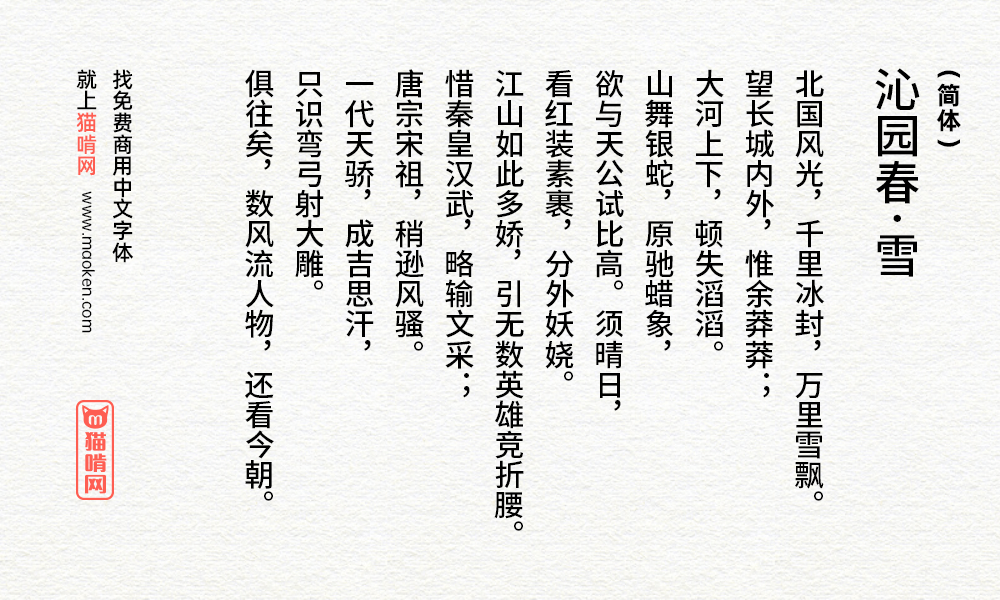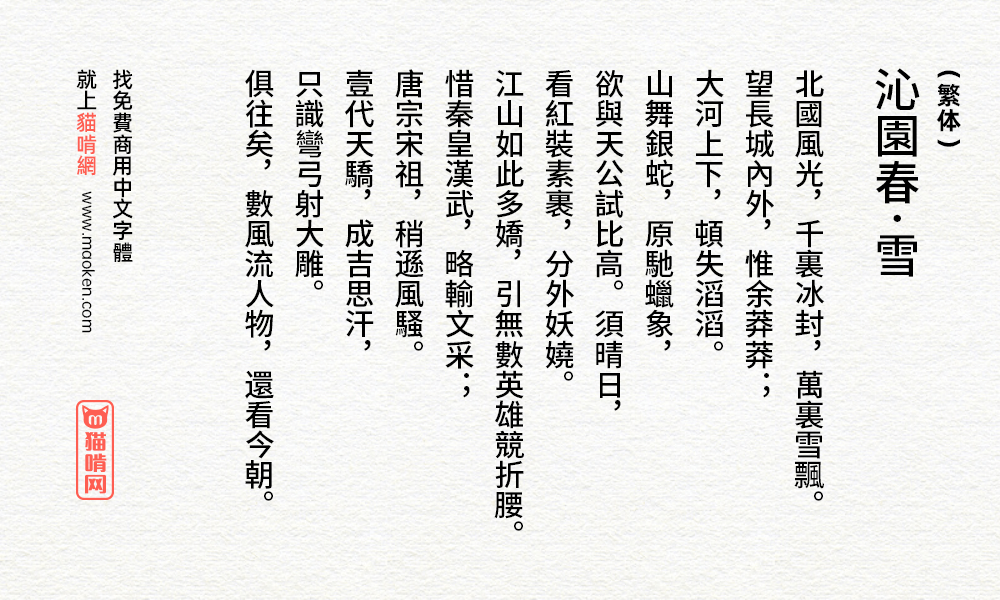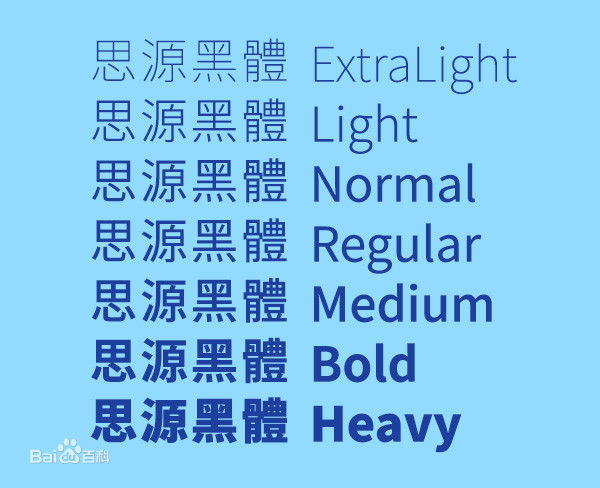
思源黑体:Adobe与谷歌开发的大名鼎鼎的免费商用字体
字体作者:Adobe & Google (美国) 字体字重:7个
思源黑体于2021年04月28日更新2.004版本,这个版本增加了思源黑体可变字体版本。关于思源黑体可变字体的介绍可以点击这里查看介绍。
说起思源黑体,也不用太多的介绍了,估计做设计的朋友们应该都会知道这款字体。这是Adobe与Google历时三年在2014年7月宣布推出的一款开源字体,这种字体有七种字体粗细(ExtraLight、Light、Normal、Regular、Medium、Bold 和 Heavy),完全支持繁体中文、简体中文、日文和韩文,这些全部都包含在一种字体中。
思源黑体有两个版本,一个是Adobe发布的版本,一个是谷歌发布的版本。这两个版本有什么不同呢?
1、字体名称不同
这两个版本的区别是字体的名称不同。Adobe版本在PS中显示的字体名称是“思源黑体”,而谷歌版本在PS中显示的字体名称是“Noto Sans CJK”
2、字重的名称不同
Adobe版本的字重名称是:ExtraLight、Light、Normal、Regular、Medium、Bold 、Heavy。
Google版本的字重名称是:Thin、Light、DemiLight、Regular、Medium、Bold、Black
关于本站提供的思源黑体行高修正版
只能说现在版本的思源黑体有些不太适合Android系统了,虽然Android原生支持可变字体是好事,但是有些情况下括号和句号会因为一些opentype特性叠在一起,这种显示效果并不好,而且看惯了某些厂商定制版字体再看思源黑体就会觉得这字体咋黏糊糊的,不过还是那句话,众多开源中文字体里面思源黑体仍是天花板……
思源黑体更新了2.005R版,但有了别的黑体,对思源黑体没啥兴趣了……
• 习惯了OPPOSANS的简洁、悠黑的完美灰度、荣耀SANS/小米兰亭pro的均匀骨架、冬青黑体的人文、苹方的六边形全能,再看思源的各种小缺点小瑕疵实在不习惯,现在开源领域的械黑/IBMPlexSans质量都比思源SC好,而且OPPOSANS/MiSans/荣耀SANS/阿里惠普都是免费商用的,字集大字重又多,不管哪方面思源都没任何竞争力了
• 只能说一开始中文字体市场正好缺一套免费的、质量还说得过去的字体,思源黑体一出现瞬间炸开了锅,但现在华米OV耀各自都定制了字体,个个都卷到极致,都免费商用,思源自然没什么优势了,再加上思源黑体的主导设计是小日子那边负责的,审美上本来就跟咱们不一样(这也就是你第一眼看它就不太顺眼的原因之一),还有我看到有人说冬青黑体,这冬青黑体更没必要提了,那玩意儿实际上比思源黑体还那啥,方正兰亭黑、汉仪旗黑的作者齐立还发文批评过,思源黑体的问题都没它严重,当年各大手机厂商也只有锤子看上冬青黑体,后面锤子自己都改用方正悠黑了,虽然后面腾祥、汉仪重新发布了7字重新版本,但是基本见不着实际使用的……
• 锤子没用方正悠黑,是把方正悠黑优化了下修改成锤子T黑,个人感觉质量比原版方正悠黑高很多,比如把不舒服的出脚衬线都去掉,更适合屏显,不过悠黑系的笔画竖勾里的脚实在不好看,又短又弯,软绵绵似的支撑不住重量
华文(就是那个代工中文版的)把常州的笔画丢尽了,相比日文版一大堆重心不稳+无意义修改。。。
• 没错,衍生自KR&JP版思源的源样黑体和SC版相比简直高下立判,华文早期给乔帮主做的华文黑体质量都比SC版思源好N倍,其实就是没用心
• 主要是华文把很多零部件原创了一遍,但你仍能感受到这是日文字体改的,属实是没必要,不过好在2.0版本修正了一些在1.0版里特别丑的,比如廴这个部首(估计是文鼎要做港版字形,顺道修复了一些偏旁部首),也有改砸了的,比如“对”、“叶”、“吔”(字形标准都弄错了)“坏”(本来没啥,就是日版也不好看),只希望3.0版能再掰回来一些吧,顺道把真正没必要改的给掰回去(有文鼎操刀的话我觉得不难),比如“心”、“个”、“全”等字,也不是说多难看,但就是觉得完全没必要改,你华文这么爱改要么就重做一套去掉日文特征的新字体得了,这改的既不像华文又背离了原版的设计理念,只是有生之年能不能见到3.0就不知道了,毕竟如今的思源黑体早不像当年那么流行了
• 现在完整支持GB18030-2022 L2了。(其实之前也没缺几个字)
在Github有更新2.001版本,並且港台的「辶」已改良,並添加了香港版本。
我發現香港跟台灣的字形差異:「着」的字形中,台灣仍舊是大陸字形,香港則是舊字形